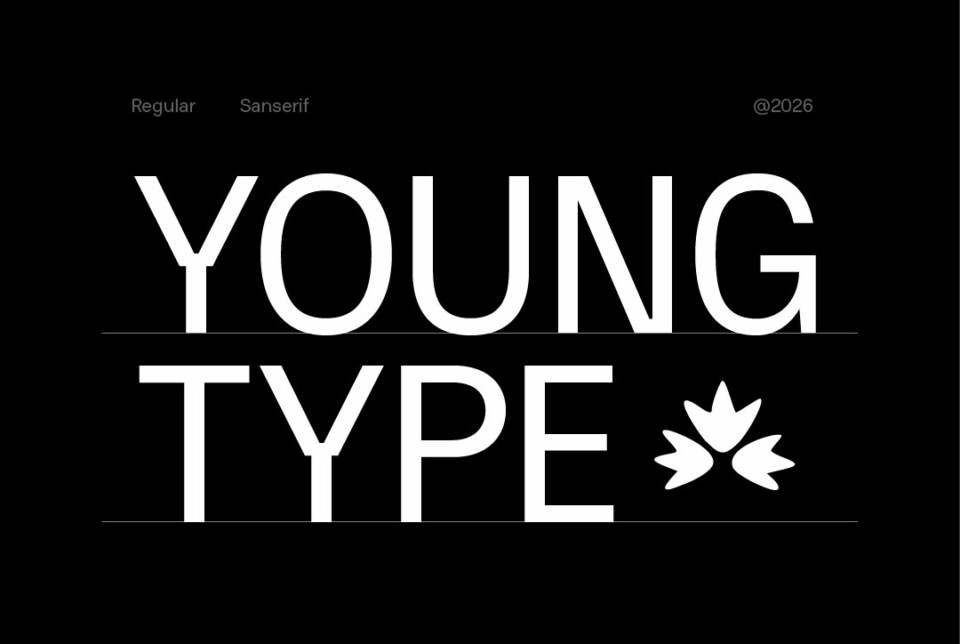
Tìm Kiếm Font Tiếng Việt YOUNG Miễn Phí Và Đẹp Nhất Cho Thiết Kế Ngay Hôm NayGiới thiệu về Font Tiếng Việt YOUNG trong thiết kế hiện đạiTrong kỷ nguyên số, việc lựa chọn một Font Miễn Phí để làm nổi bật thông điệp là vô cùng quan trọng đối với các bạn học sinh và nhà trường. Font Tiếng Việt YOUNG chính là một giải pháp hoàn hảo nhờ phong cách thiết kế hiện đại, năng động và tràn đầy năng lượng tươi trẻ. Bộ mã hóa chuẩn giúp phông chữ này không bị lỗi hiển thị khi gõ dấu, mang lại sự tối ưu tuyệt đối cho mọi sản phẩm đồ họa truyền thông trường học.Những đặc điểm nổi bật giúp Font Tiếng Việt YOUNG được yêu thíchThiết kế đường nét tinh tế và dễ đọcBộ font này sở hữu các đường nét bo tròn mềm mại kết hợp cấu trúc hình khối vững chắc. Sự kết hợp độc đáo giúp văn bản vừa giữ được sự nghiêm túc cần có trong môi trường giáo dục, vừa mang lại cảm giác thân thiện, dễ tiếp cận cho người xem.Khả năng ứng dụng đa dạng trong học đườngBạn có thể dễ dàng ứng dụng phông chữ này vào rất nhiều mục đích khác nhau. Từ việc thiết kế slide bài giảng điện tử sinh động, làm báo tường, cho đến sáng tạo áp phích cho các sự kiện Đoàn, Đội đều mang lại hiệu ứng thị giác cực kỳ bắt mắt.Cách tải và sử dụng Font Tiếng Việt YOUNG hiệu quả nhấtLưu ý khi phối hợp màu sắc văn bảnĐể font chữ phát huy tối đa vẻ đẹp, bạn nên kết hợp với các tông màu tươi sáng như xanh dương, cam hoặc xanh lá. Tránh dùng quá nhiều hiệu ứng đổ bóng phức tạp làm giảm đi sự tối giản, tinh tế nguyên bản của các nét chữ.Kết luận về bộ phông chữ dành cho thế hệ trẻTóm lại, bộ Font Tiếng Việt YOUNG là một lựa chọn không thể bỏ qua nếu bạn đang tìm kiếm sự phá cách nhưng vẫn giữ được nét thanh lịch. Hãy truy cập ngay kho dữ liệu Font Miễn Phí, Font Việt Hóa, Font Tiếng Việt YOUNG để tải về và nâng tầm các dự án sáng tạo của mình ngay hôm nay nhé.
Font Tiếng Việt YOUNG